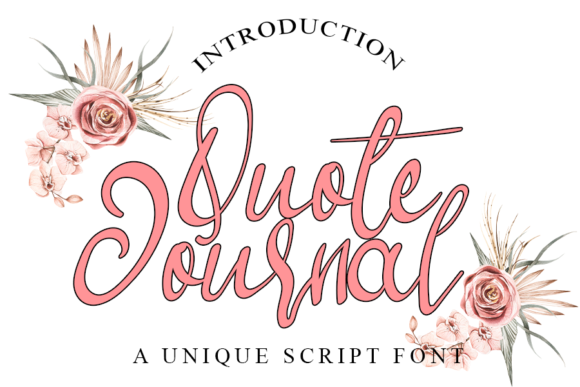
Quote Journal
Conçu avec précision, Quote Journal offre des vecteurs nets, une typographie fluide et une licence commerciale pour une tranquillité d'esprit.